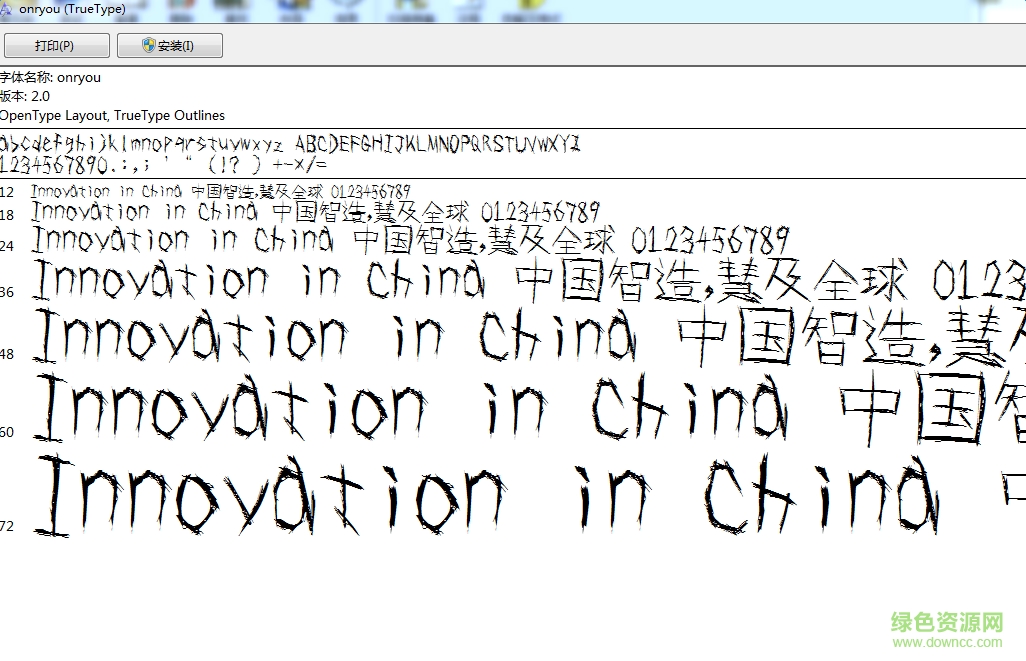
日本手寫怨霊體
日本手寫體怨霊字體是一款浪漫手寫風(fēng)格字體軟件,怨霊手寫體非常的非主流,字體筆畫無拘無束,十分清新脫俗,整體效果別有一番韻味,還有更多好看字體歡迎來綠色資源網(wǎng)下載體驗(yàn)!
日本手寫體怨霊字體是一款應(yīng)用于藝術(shù)設(shè)計(jì)方面的簡體中文字體,該字體筆畫粗壯,尾部的甩尾有力且有豐富的筆觸細(xì)節(jié),大字效果突出且引人注目;并且最大程度還原作者書寫字形,細(xì)節(jié)表現(xiàn)完整,且字庫完整,可以廣泛應(yīng)用于名片設(shè)計(jì)、新聞媒體、宣傳海報(bào)、ppt、影視制作以及內(nèi)容用字等領(lǐng)域。
日本手寫體怨霊
該字體筆畫隨意,每個(gè)字體用毛邊突出,給人非常時(shí)尚非主流的感覺,非常適合裝逼哦!